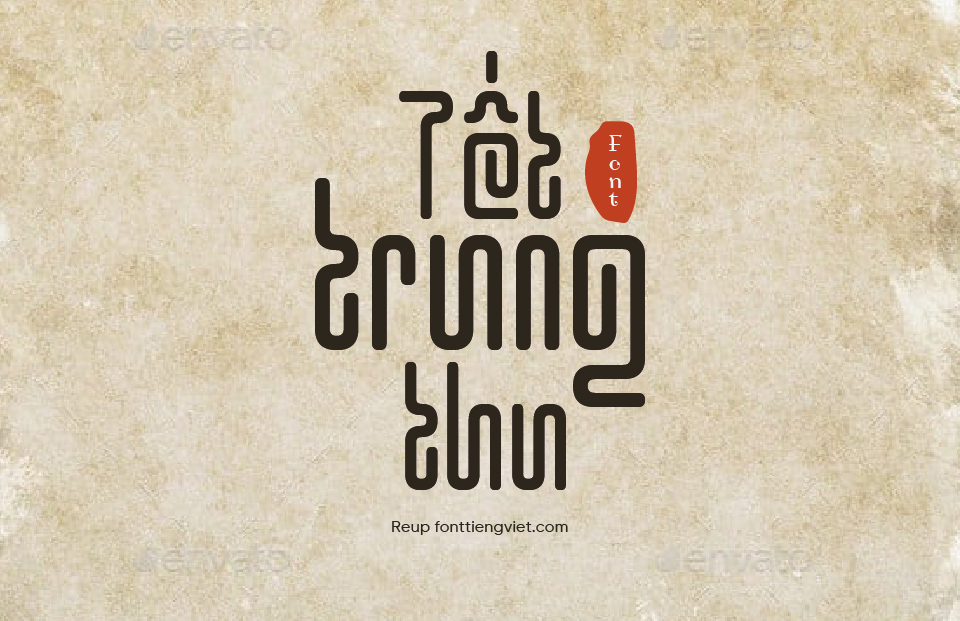
Font Việt hóa LNTH Hieroglyphic – Font trung thu
Font Việt hóa LNTH Hieroglyphic – Font trung thu Độc Đáo Cho Mùa Lễ Hội
Giới thiệu về Font Việt hóa LNTH Hieroglyphic – Font trung thu
Mùa Tết Trung thu đang đến gần, nhu cầu thiết kế các ấn phẩm văn hóa như lồng đèn, thiệp mời hay banner sự kiện ngày càng tăng cao. Để tạo nên dấu ấn riêng biệt, việc lựa chọn Font Miễn Phí phù hợp là vô cùng quan trọng. Font Việt hóa LNTH Hieroglyphic – Font trung thu chính là giải pháp hoàn hảo giúp các bạn học sinh và thầy cô tạo nên những tác phẩm đậm chất truyền thống nhưng không kém phần sáng tạo.
Đặc điểm thiết kế của Font Việt hóa LNTH Hieroglyphic – Font trung thu
Bộ font này được lấy cảm hứng từ những nét vẽ tượng hình cổ xưa, kết hợp khéo léo với cấu trúc chữ hiện đại. Với các đường nét uốn lượn mềm mại, Font Việt hóa LNTH Hieroglyphic – Font trung thu mang đến cảm giác hoài cổ, gợi nhớ về những câu chuyện dân gian dưới ánh trăng rằm. Đặc biệt, bộ font đã được tối ưu hóa tiếng Việt hoàn chỉnh, giúp việc soạn thảo nội dung không bị lỗi dấu, đảm bảo tính thẩm mỹ cao nhất cho bản thiết kế.
Ứng dụng thực tế trong giáo dục và trang trí
Trong môi trường học đường, mẫu chữ này rất được ưa chuộng để làm bảng tin lớp học hoặc các bài thuyết trình về chủ đề lễ hội. Nhờ phong cách độc đáo, Font Việt hóa LNTH Hieroglyphic – Font trung thu giúp thông điệp trở nên sinh động và thu hút sự chú ý của các em nhỏ. Ngoài ra, các nhà thiết kế tự do cũng có thể sử dụng font này để tạo ra các bao bì bánh trung thu mang phong cách nghệ thuật cổ điển.
Cách sử dụng font hiệu quả
Để phát huy tối đa vẻ đẹp, bạn nên kết hợp font với các tông màu ấm như đỏ, vàng hoặc cam. Đừng quên điều chỉnh khoảng cách chữ sao cho thoáng đãng để giữ được độ đọc tốt nhất trên mọi kích thước in ấn.
Kết luận về bộ font chữ đẹp